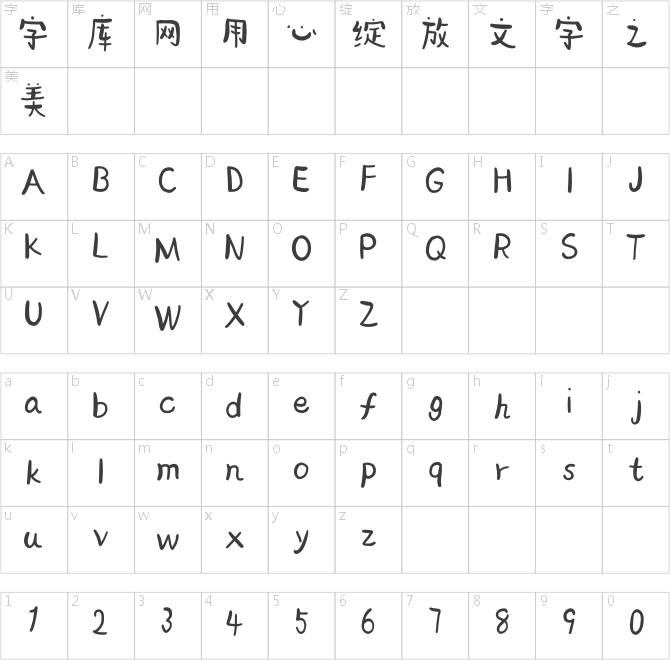
造字工房新俏体 详情页
字体名称: 造字工房新俏体
造字工房新俏体,结体松散恣意,笔画处理不拘一格,个性突出。整体效果灵妙幼拙、天真可爱,极生动之致。适用于儿童读物、报刊杂志标题、广告设计、个性招牌等视觉环境,有着极强的应用空间。本字体为简体字库,采用OpenType/CID格式,Adobe-GB1-5编码。基于中华人民共和国GB2312-80字符集标准,另按需添加101个汉字。共收容字数6864CJK汉字,ASCII常用字符100个。